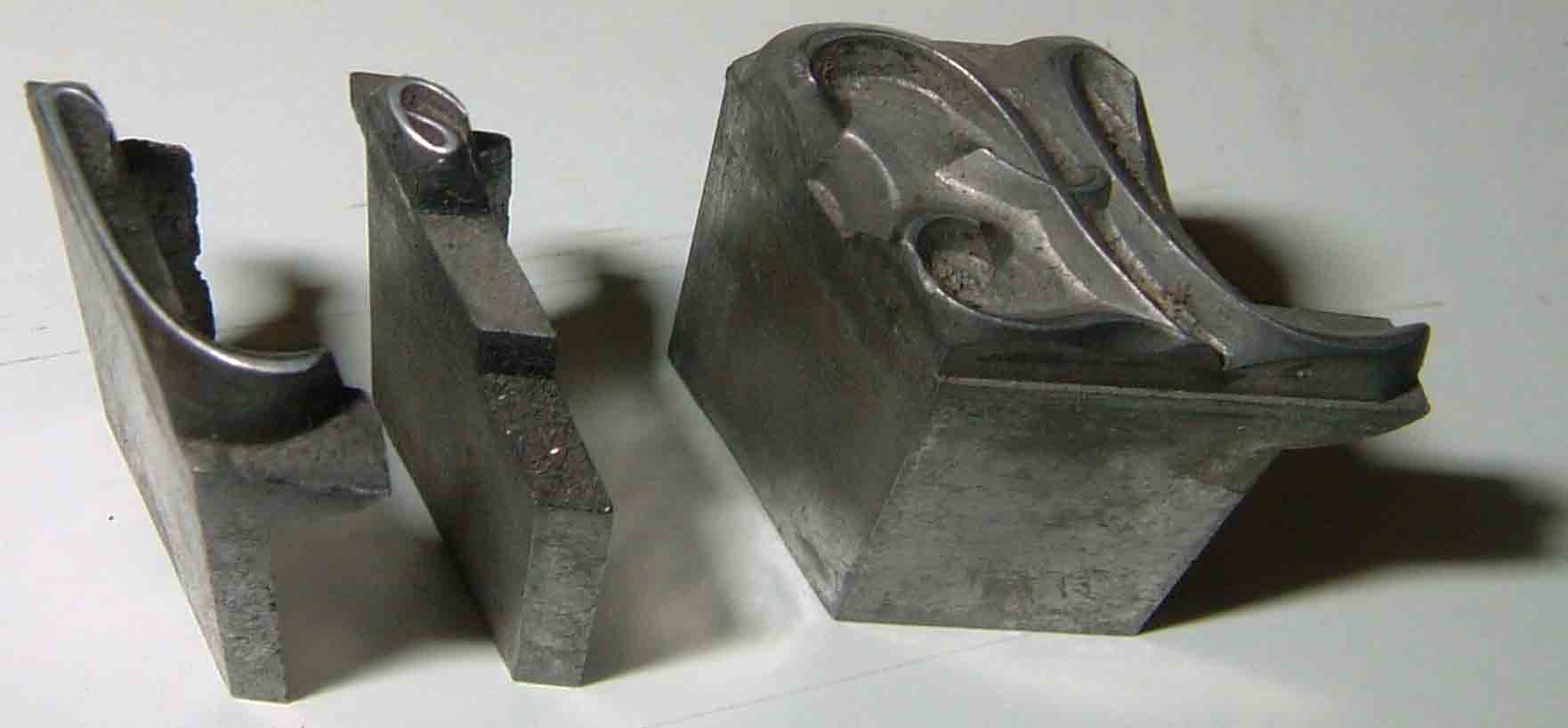
Réponse au message de "Jacques André" <jacques.andre@xxxxxxxx> To: <typographie@xxxxxxxxxxxxxxx> Sent: Monday, May 17, 2004 2:50 PM Subject: Re: [typo] plomb et approche > Mais en fait, cette notion d'approche n'a pas de sens avec des boîtes > verticales pour des caractères en italique qui débordent (l'idéal, même > au plomb serait d'utiliser des boîtes oblique comme le fit Didot pour > son anglaise). > Oui, mais même là, ça déborde de tous les côtés... Cf. image. :-) Christian Laucou.